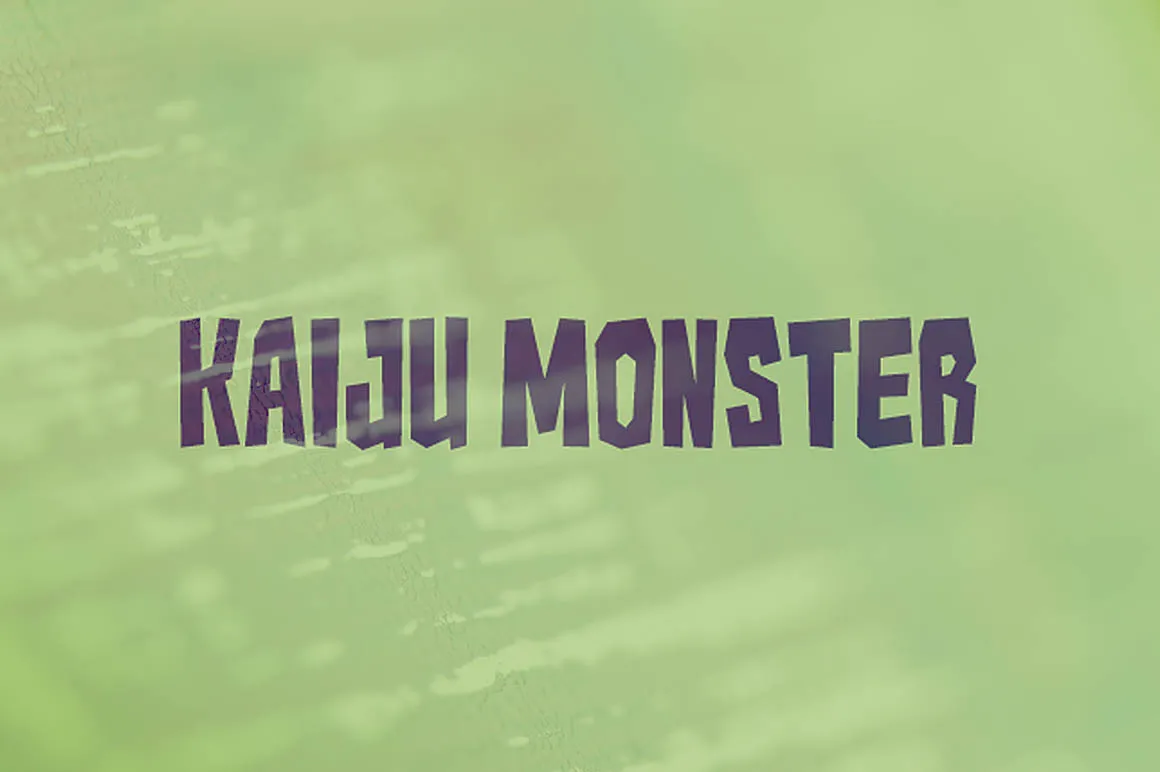
Kaiju Monster Font – Download Grátis
A fonte Kaiju Monster, criada pelo designer Hamilton, é uma escolha ideal para quem busca expressar um estilo moderno ou futurista que se adequa perfeitamente à categoria de Graffiti Fonts. Esta fonte tem sua origem na Goma Shin e oferece uma aparição única e inovadora. Um dos pontos fortes desta fonte é o seu design inspirado em kaiju, criaturas de ficção que podem ser descritos como gigantes monstros animados pelos raios solares ou por algum tipo de alienígena tecnológico. Se você está procurando por uma fonte para adicionar um toque único e criativo a seu design, especialmente se for em um contexto gráfico urbano ou street art, a fonte Kaiju Monster é definitivamente um investimento valioso. Hamilton trouxe um estilo futurista ao seu trabalho com essa fonte, que parece ter sido inspirado por uma explosão de cores e formas geométricas modernas. A Goma Shin apresenta aqui uma coleção diversificada de recursos gráficos, incluindo fontes que se adaptam perfeitamente a ambientes urbanos e graffiteiros. A cada visual da fonte Kaiju Monster é uma explosão de cores vibrantes e formas únicas, tornando-a não apenas um recurso útil, mas também um componente incrivelmente atraente para qualquer projeto gráfico moderno e vanguardista.